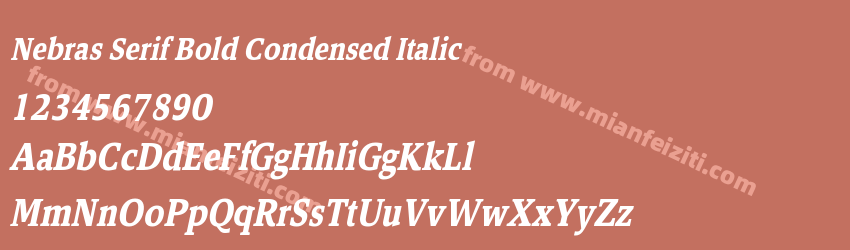
Nebras Serif Bold Condensed Italic
字体名称: Nebras Serif Bold Condensed Italic
Postscript名称: NebrasSerif-BoldCondensedItalic
本款“Nebras Serif Bold Condensed Italic”是一款书写很新颖的字体,字体大方,适合各种设计作品使用!欢迎下载!